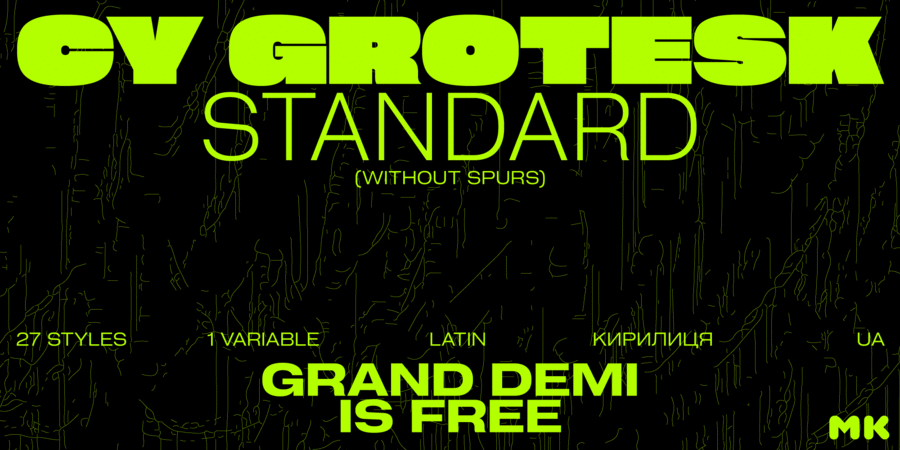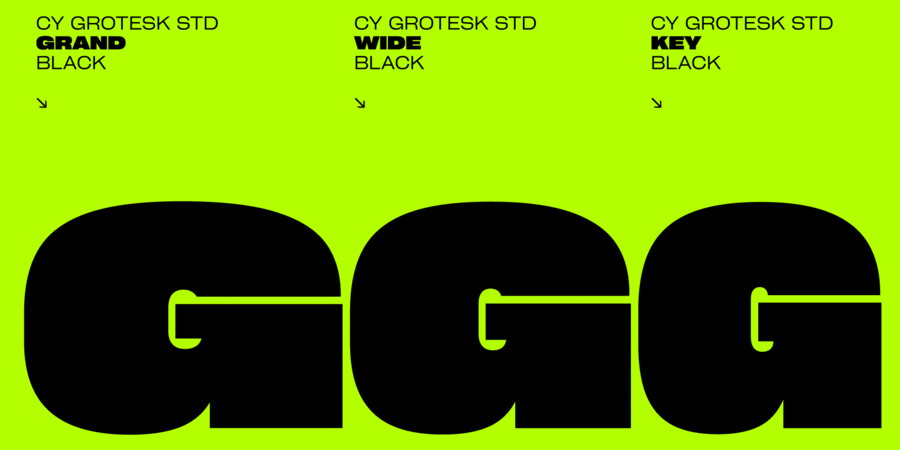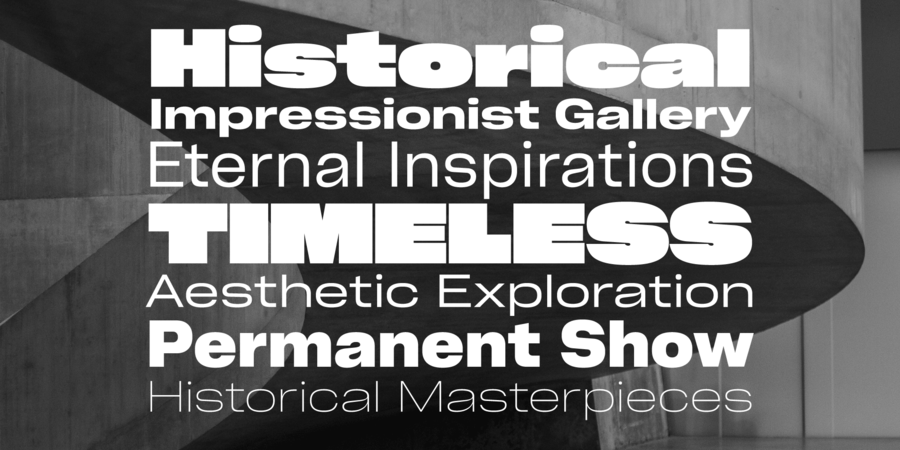
Cy Grotesk Std – модифікована версія оригінального Cy Grotesk, що пропонує нейтральніший і більш конвенційний формат неогротеску. Відсутність довгих гострокутих шпор у літерах — її ключова відмінність від першоджерела, що дає чистішу й більш універсальну естетику.
Це акцидентний шрифт із ексцентричним характером та особливим ритмом. Символи мають плавні вигини та закриту апертуру, урівноважені великими клиноподібними розрізами між півовалами та стемом. Зібраний як багатофункціональна робоча конячка, Cy Grotesk Std має широкий спектр застосування. Шрифтове сімейство складається з 27 накреслень, які варіюються за товщиною та шириною та 1 варіативного шрифта з 2 осями. Від чистого й тонкого до радикально наджирного. Від місткого Key до кричущого Grand. Всі накреслення підтримують розширену латинку і базову кирилицю. Характеристики: набір гліфів: 682; 27 накреслень (3 ширини × 9 товщин) + варіативний; Підтримка 210+ мов; Latin Extended; Cyrillic Basic. OpenType-можливості: Верхній і нижній регістри; Пропорційні, обведені в коло, табличні цифри, верхні й нижні індекси, дроби; Пунктуація та символи; Стрілки; Стилістичні набори (ss01–ss10); Лігатури; Форми, чутливі до регістру. Накреслення Cy Grotesk Std Grand Demi є безкоштовним для безлімітного використання на умовах ліцензій «Десктоп» і «Веб». Шрифт розробив Максим Кобузан у 2025 році. Світ ловив мене, та не спіймав!
журнал, лендінг, плакат, обкладинка, інструкція, газета, айдентіка, презентація, технічна документація, візитка, цінник, мем, етикетка, реклама, пакування, вивіска, афіша, оголошення, відео, меню, комікс, стікер, наліпка Адаптованість гарнітури до носіїв:
Асоціації з сімейством шрифтів Cy Grotesk StdОсобистість і характер гарнітури:
спокійний, доступний, комфортний, Простий, глобалізований, глобалістічний, чистий, легкий, прохолодний, свіжий, модний, міський, тонкий, сучасний, ясний, рівний, зрозумілий, якісний, різкий, чіткий, логічний, точний, звичайний, стандартний, скляний, прозорий, дротяний, худий, формальний, серйозний, інженерний, креслярський, твердий, солідний, мотивуючий, переконливий, сильний, залізний, сталевий, міцний, яскравий, важкий, впевнений, стійкий, потужний, помітний, активний, важливий, гострий, техногенний, значний, мужній, кондовий, суворий, добротний, щільний, монументальний, технічний, гучний, сміливий, брутальний, надійний, індустріальний, урбаністичний, авторитетний, діловий, крутий, залізничний, самостійний, відповідальний, західний, амбітний, обов'язковий, швидкий, рішучий, енергійний, тісний, оригінальний, характерний, незвичайний, самобутній, цікавий, динамічний, іронічний, претензійний, екстравагантний, нонконформістський, здоровий, грубий, мачо, сексуальний, бандитський, дотепний, чорний, карикатурний, товстий, наполегливий, масивний, громіздкий, дивний, епатажний, експериментальний, дзвінкий, нав'язливий, екстремальний, ризикований, вуличний, вибуховий, зухвалий, хуліганський, кричущий, кінематографічний, жорсткий, ігровий, радикальний, нахабний, прямокутний, спортивний
прилад, суспільство, Місто, лосьйон, шампунь, мода, інновації, дизайн, одяг, коворкінг, небо, вода, чистота, взуття, інженер, техніка, наука, хімія, фізика, транспорт, бізнес, автобус, торгівля, магазин, реклама, поліція, новини, політика, інструмент, енергетика, паливо, електростанція, сейф, екскаватор, металургія, верстат, вантажоперевезення, порт, тренажери, вантажівка, далекобійник, двигун, урбаністика, промисловість, машинобудування, завод, автомобіль, мотор, прес, вагон, авіація, літак, залізниця, ралі, авто, тачки, комп'ютерна гра, кіно, склад, тара, вантаж, будівництво, Футбол, детектив, мафія, карти, гра, алкоголь, віскі, м'ясо, джинси, револьвер, обід, вечеря, гамбургер, коктейль, Барбершоп, Інстаграм, вечір, розваги, атракціон, селфі, танк, страйкбол, блокбастер, бойовик, екшен, шутер, цегла, сталевар, шахтар, інсектицид, закуска, фаст фуд, каскадер, екстрим, бомба, казино, реп, концерт, супергерой, дискотека, шолом, гонки, спорт, архітектура, конструктор, позашляховик, нафта Гарнітура має ознаки стилів: